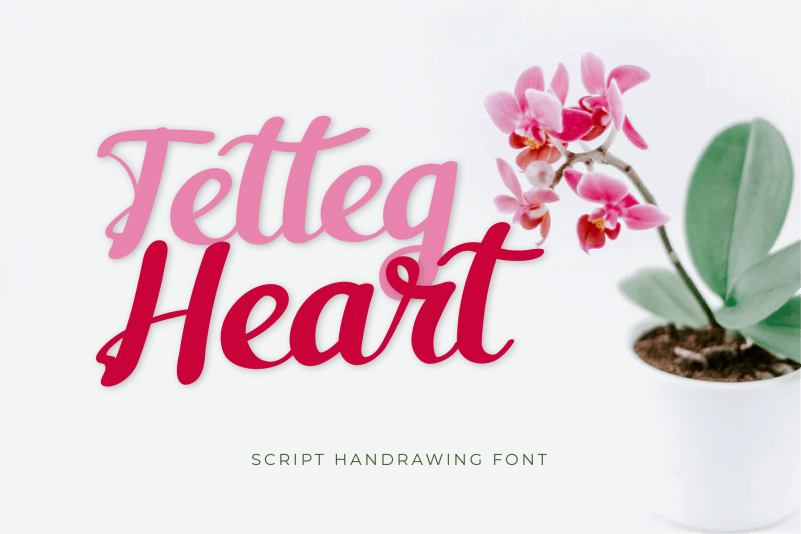
Tetteg Heart Script Font – Download Grátis
A Tetteg Heart Script Font é uma deliciosa novidade para quem adora fazer letras elaboradas com um toque romântico. Desenvolvida pelo designer twinletter, essa fonte de escrita chama atenção por sua expressão emocional e delicadeza. Ideal para aqueles que buscam uma fonte única capaz de criar textos realmente especiais. Com uma aparência charmosa e fluida, a Tetteg Heart Script Font é perfeita para design gráfico personalizado ou até mesmo para adicionar um toque romântico em seus projetos digitais pessoais. Não esqueça que o fonte é totalmente gratuito para uso pessoal. Para quem deseja apoiar o desenvolvimento e manutenção dessa bela fonte, existe uma opção de doação através do PayPal, com a conta disponível no link fornecido. Esta página de download destaca exatamente como você pode adquirir e começar a usar essa linda fonte. Seja para fins pessoais ou profissionais, a Tetteg Heart Script Font trará uma nova dimensão ao seu design gráfico, oferecendo textos com um toque personalizado e emotivo.